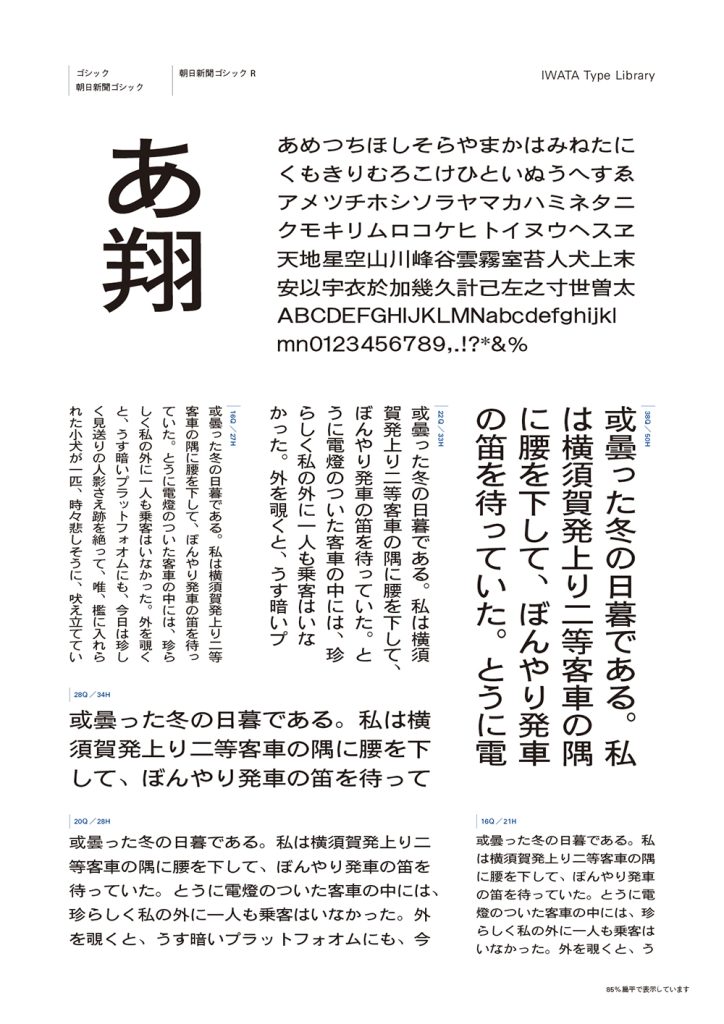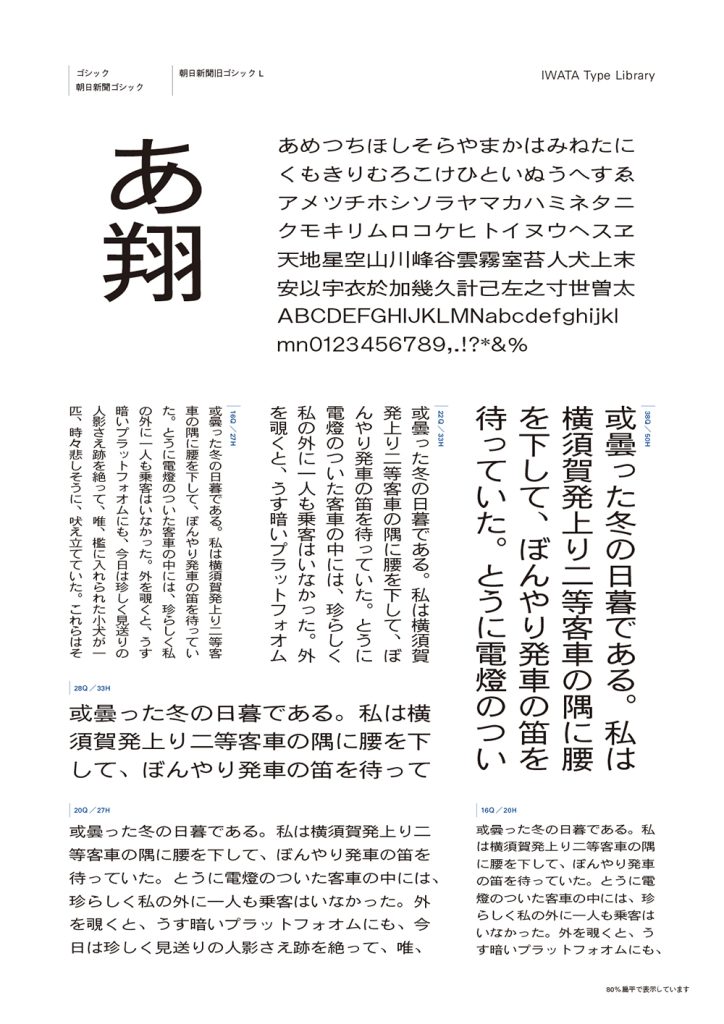
筆の自然な流れを生かしたかなと、広めのふところによる安定感のある、優雅さと柔軟性を兼ね備えた「凜」とした佇まいが特徴の新聞ゴシック体です。
朝日新聞の活字時代から受け継がれ、視認性を高めるために線幅や扁平率を調整しながら進化している、伝統と新しさを併せ持つ書体です。
新聞以外にも、多様な媒体で活用できる汎用性の高さも魅力です。